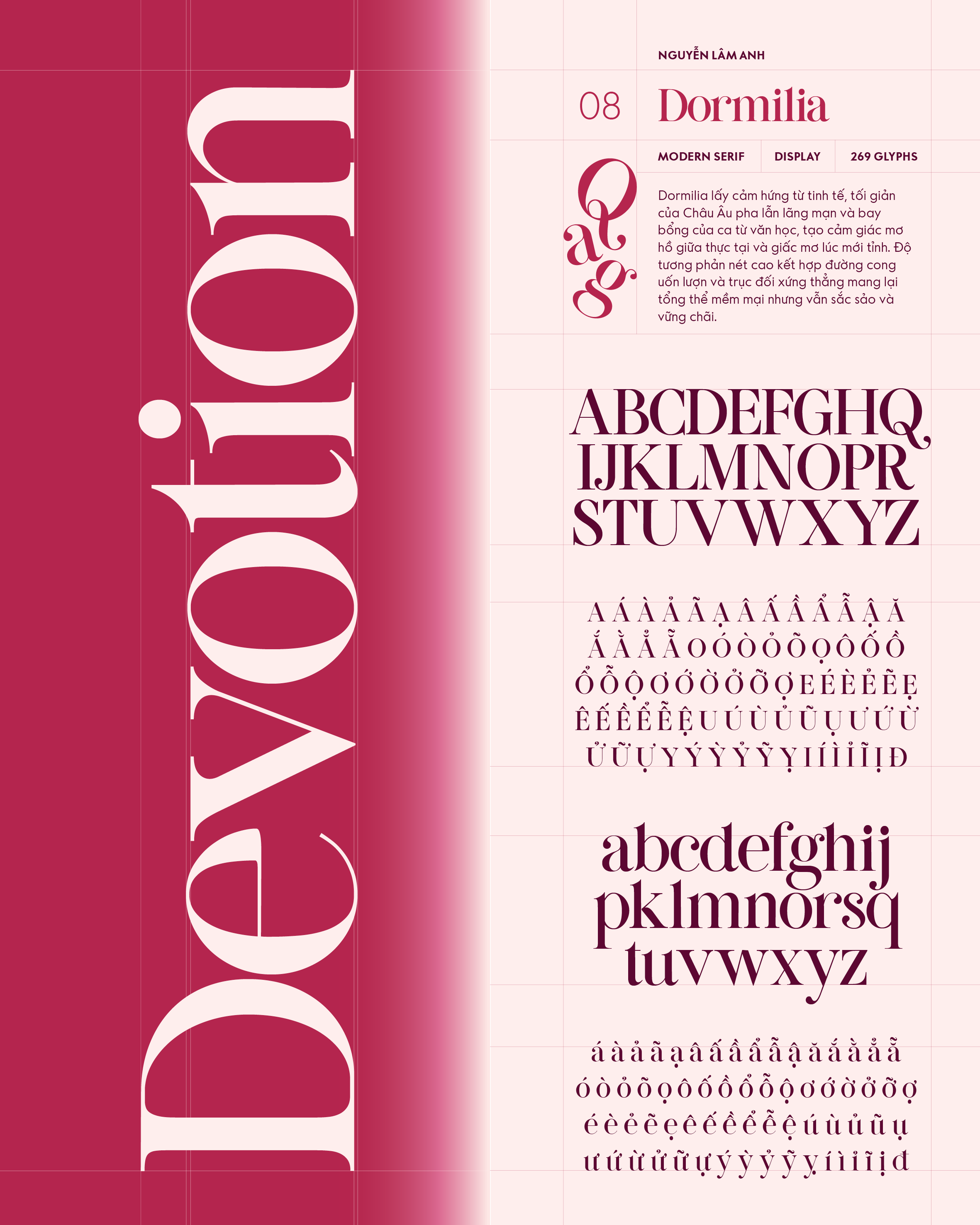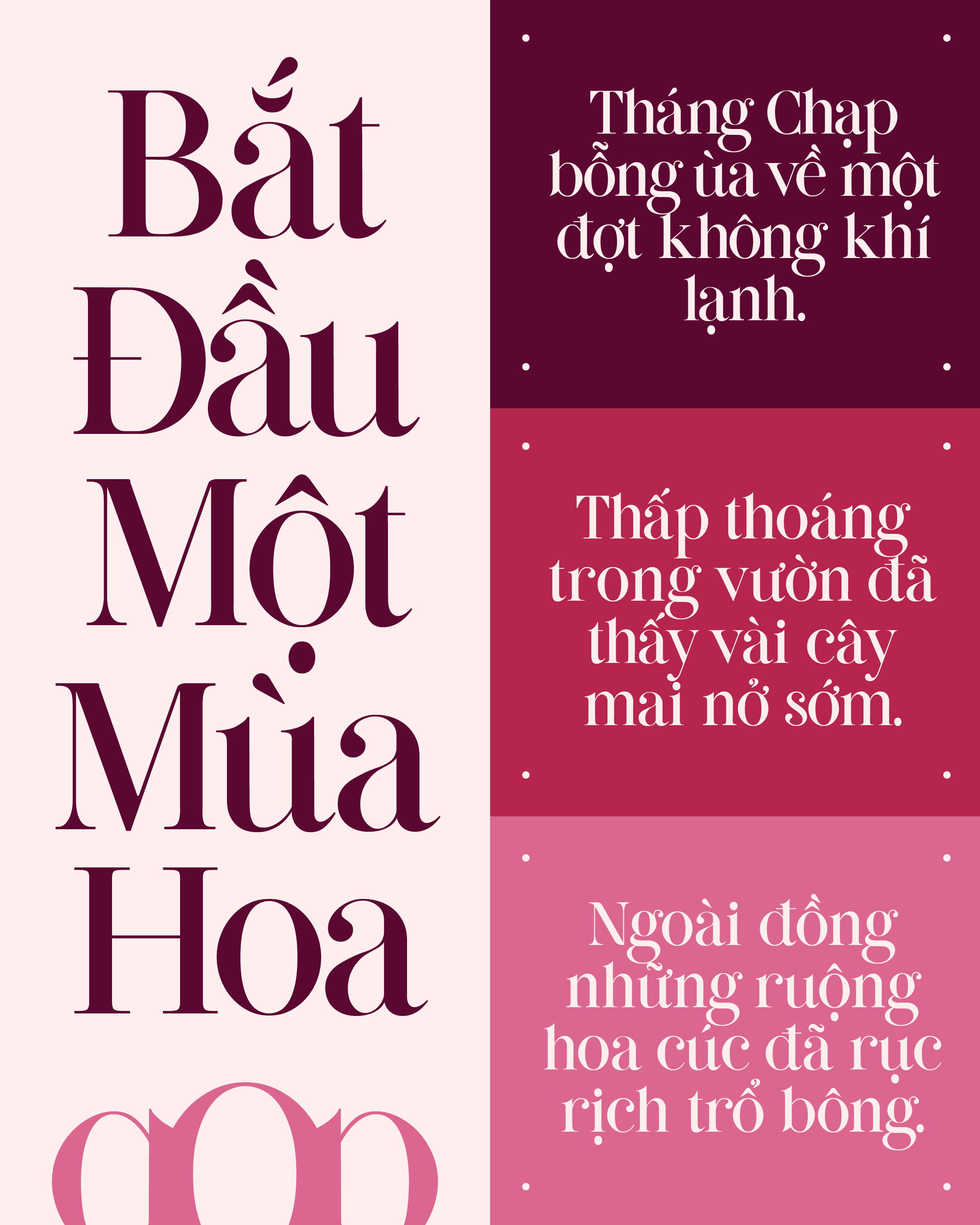
Dormilia
Về Dormilia: Dormilia lấy cảm hứng từ tinh tế, tối giản của Châu Âu pha lẫn lãng mạn và bay bổng của ca từ văn học, tạo cảm giác mơ hồ giữa thực tại và giấc mơ lúc mới tỉnh. Độ tương phản nét cao kết hợp đường cong uốn lượn và trục đối xứng thẳng mang lại tổng thể mềm mại nhưng vẫn sắc sảo và vững chãi.
Modern Serif
Display
Nguyễn Lâm Anh